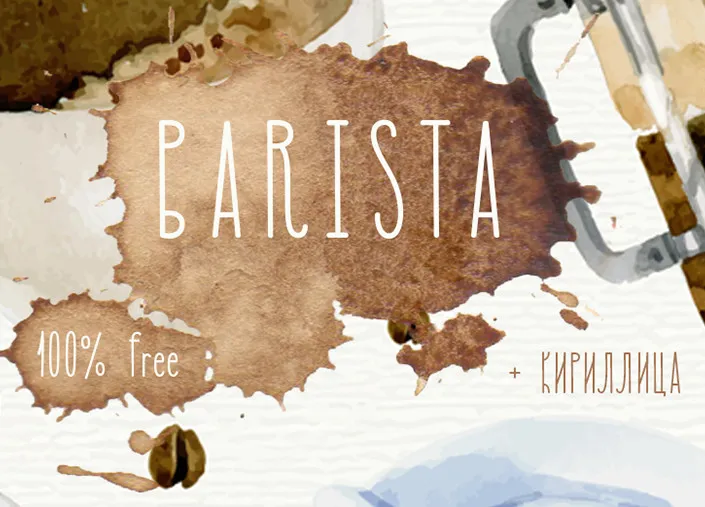
MADE Barista Typeface – Download Grátis
A MADE Barista Typeface é uma tipografia Display perfeitamente adaptada para criar texturas vibrantes e atraentes no seu design. Seja ela aplicada aos rótulos das bebidas, anúncios de eventos ou em qualquer formato visual desejado, essa fonte oferece uma escolha incrível de formas dinâmicas que certamente tornará suas criações únicas e memoráveis. Com sua tipografia livre para uso pessoal e comercial, a MADE Barista Typeface é um recurso valioso para designers profissionais e amadores. Basta entrar em contato conosco pelo email:  para obter mais detalhes sobre como integrar esta fonte vibrante e sofisticada em seus projetos.